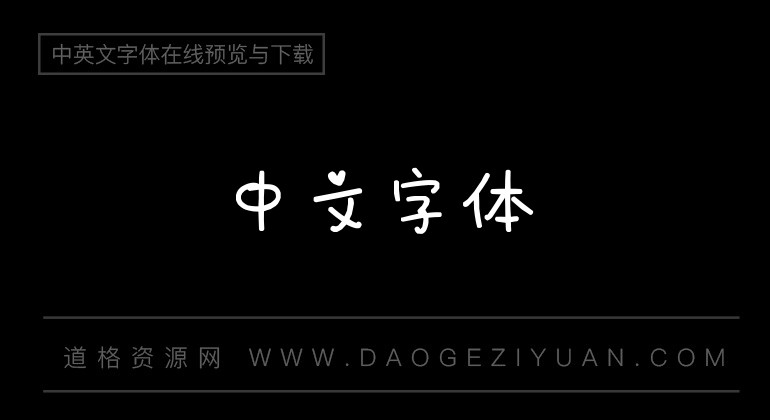
可爱得可爱
可爱得可爱字体是一款可爱的字体,它拥有柔和的线条,清晰的结构,大胆的色彩,给人以温馨、活泼的感觉。它的字体特点是圆润的线条,柔和的字形,以及非常可爱的色彩,给人以温馨、活泼的感觉。可爱得可爱字体适用于儿童类、游戏类、漫画类等等,是一款非常可爱的字体。
可爱得可爱是一款非常不错的手写艺术字体,具有很好的视觉感,适合于文化类的宣传设计、商业类品牌的广告和产品包装设计以及个性化文字排版等较多场景。
可爱得可爱字符映射图